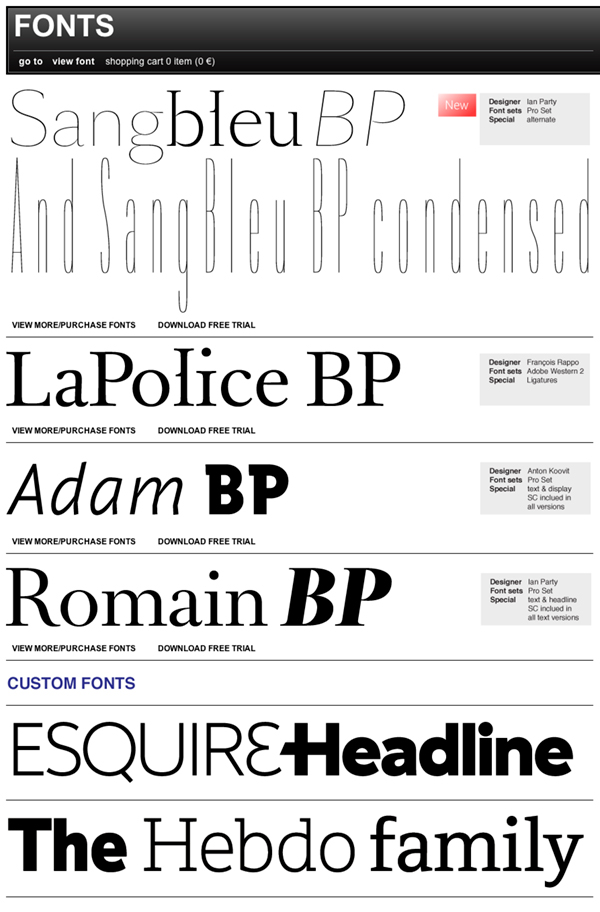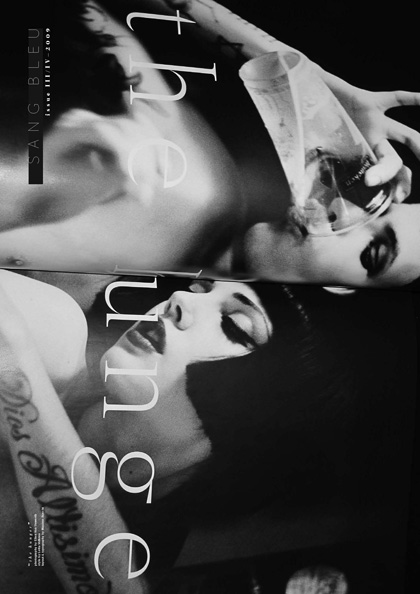
BP Foundry | Le SangBleu | une typo délicate et élégante
Ian Party qui co-dirige cette typofondrie, à l’exigence et au professionnalisme poussé à l’extrême, a bien compris qu’il ne suffit pas de dessiner des fontes magnifiques mais que nécessité fait loi, il faut aussi les faire vivre au sein d’expressions graphiques voire photographiques pour situer, donner envie et finalement faire vivre les nouvelles créations typographiques dans le monde «du réel». Il poursuit là une idée qui a fait son chemin aussi bien dans les années 80 (U&LC, Baseline, typoGabor présente, Emigre et Fuse) que plus récemment chez toutes les typofonderies sérieuses dont nous avons eu déjà l’occasion d’évoquer.
Ian Party, born in Lausanne in 1977, lives and works in Lausanne, Switzerland as a typedesigner. After studying at the ECAL (Ecole Cantonale d’Art de Lausanne) in Lausanne, Switzerland, Ian completed a master in typedesign at the Royal Academy of Arts (KABK) in The Hague.
He also is the cofounder of B&P Typefoundry and teaches type design at the ECAL, Lausanne.
Ian Party is the designer of Romain BP, Esquire, Celsian, SangBleu Display